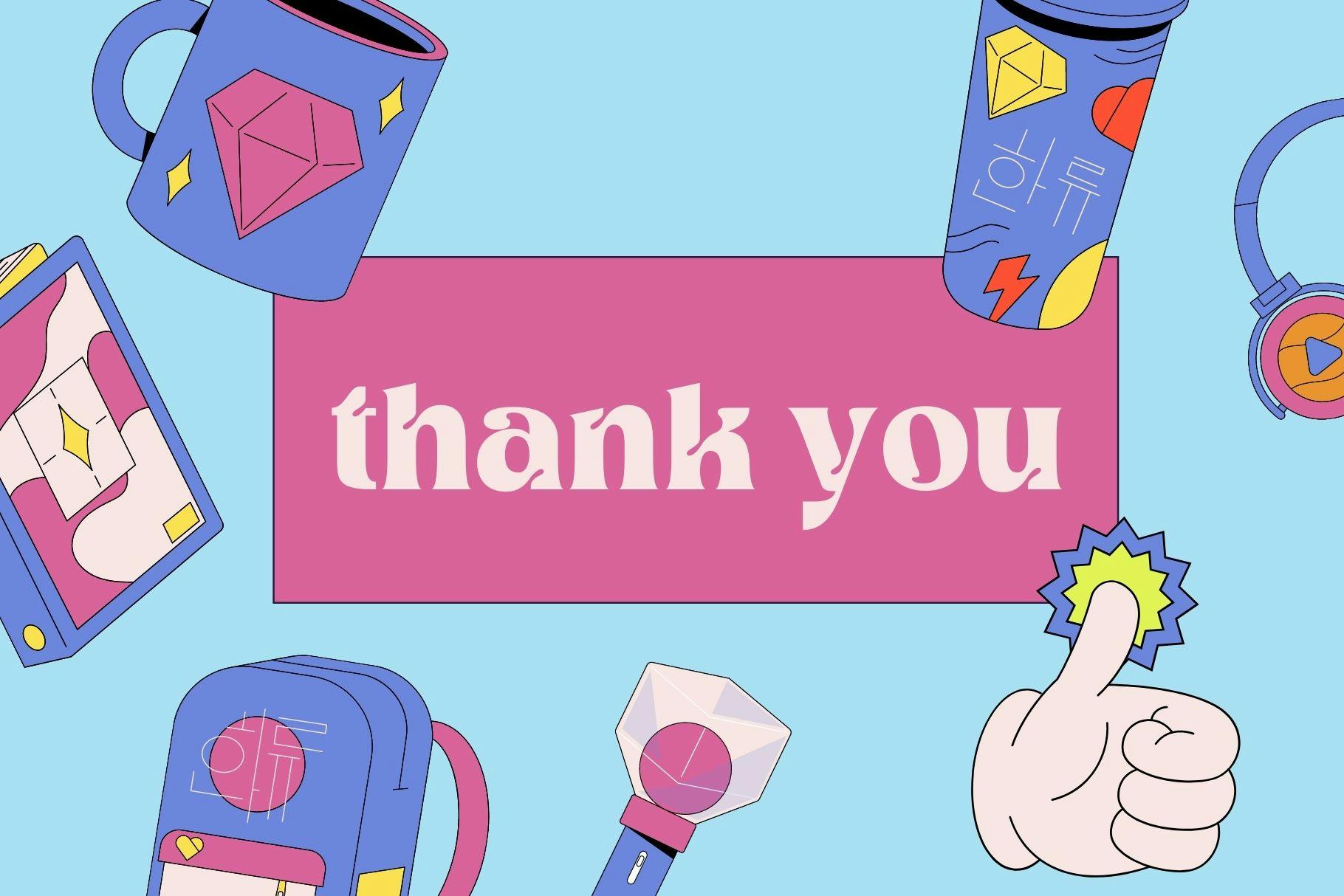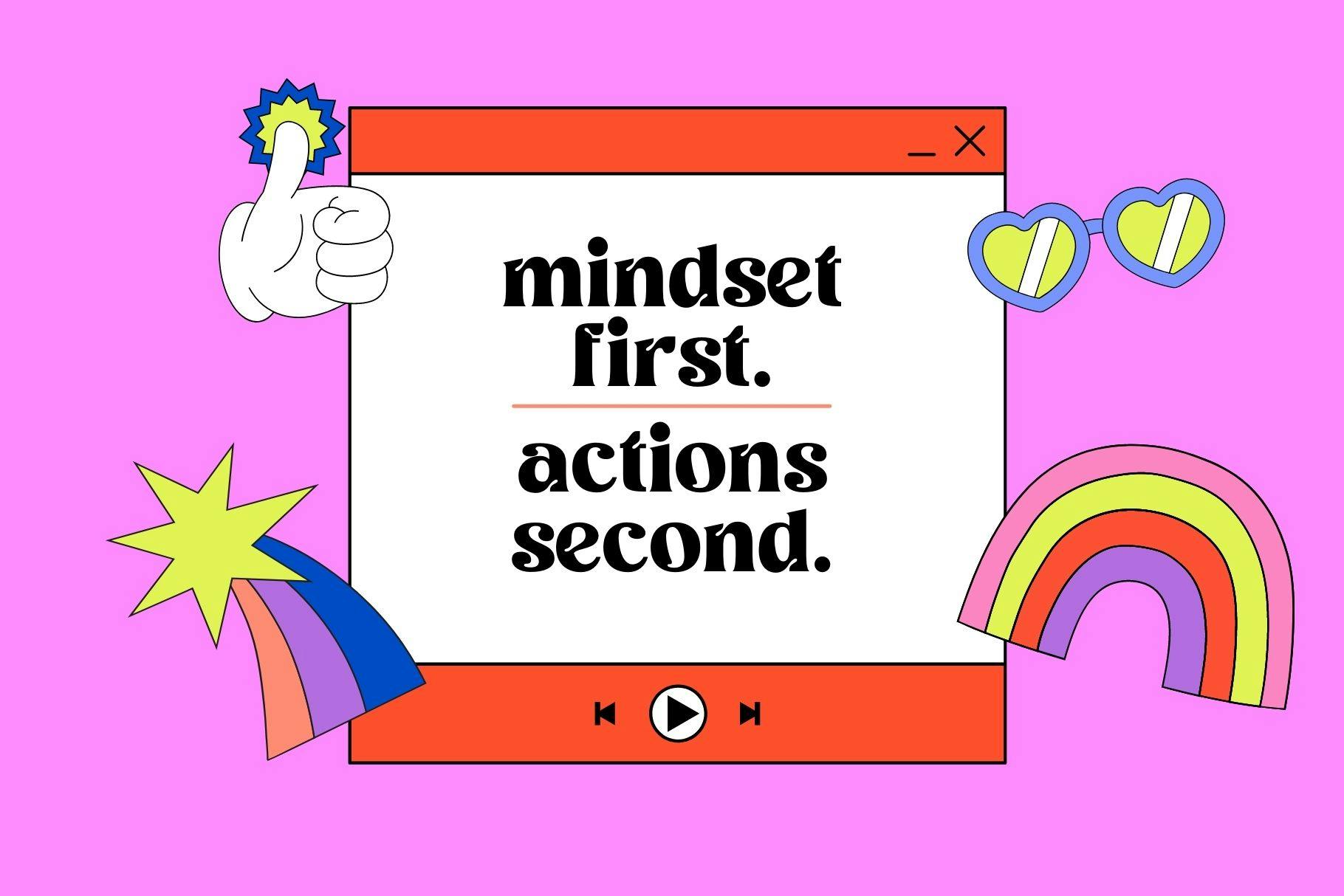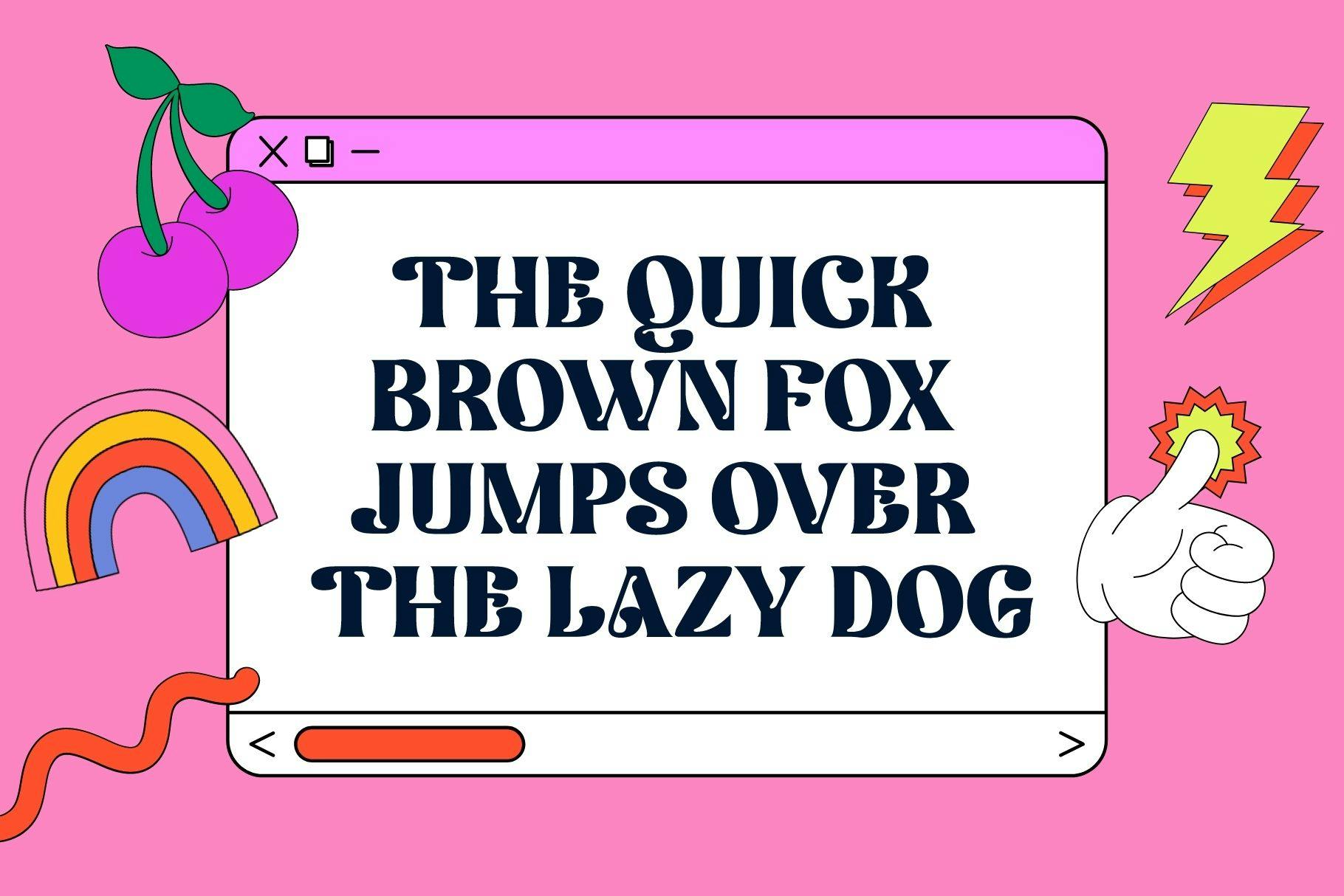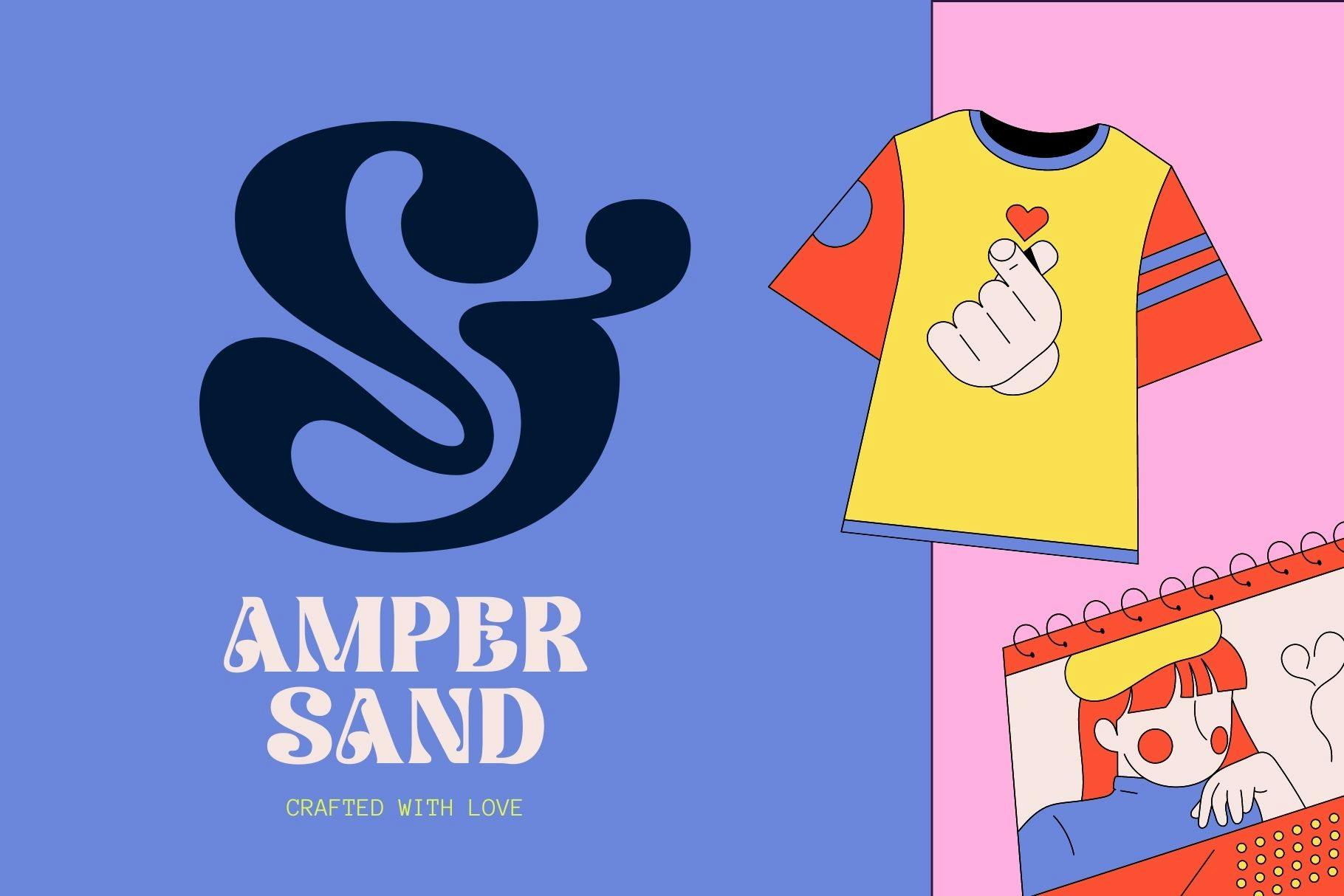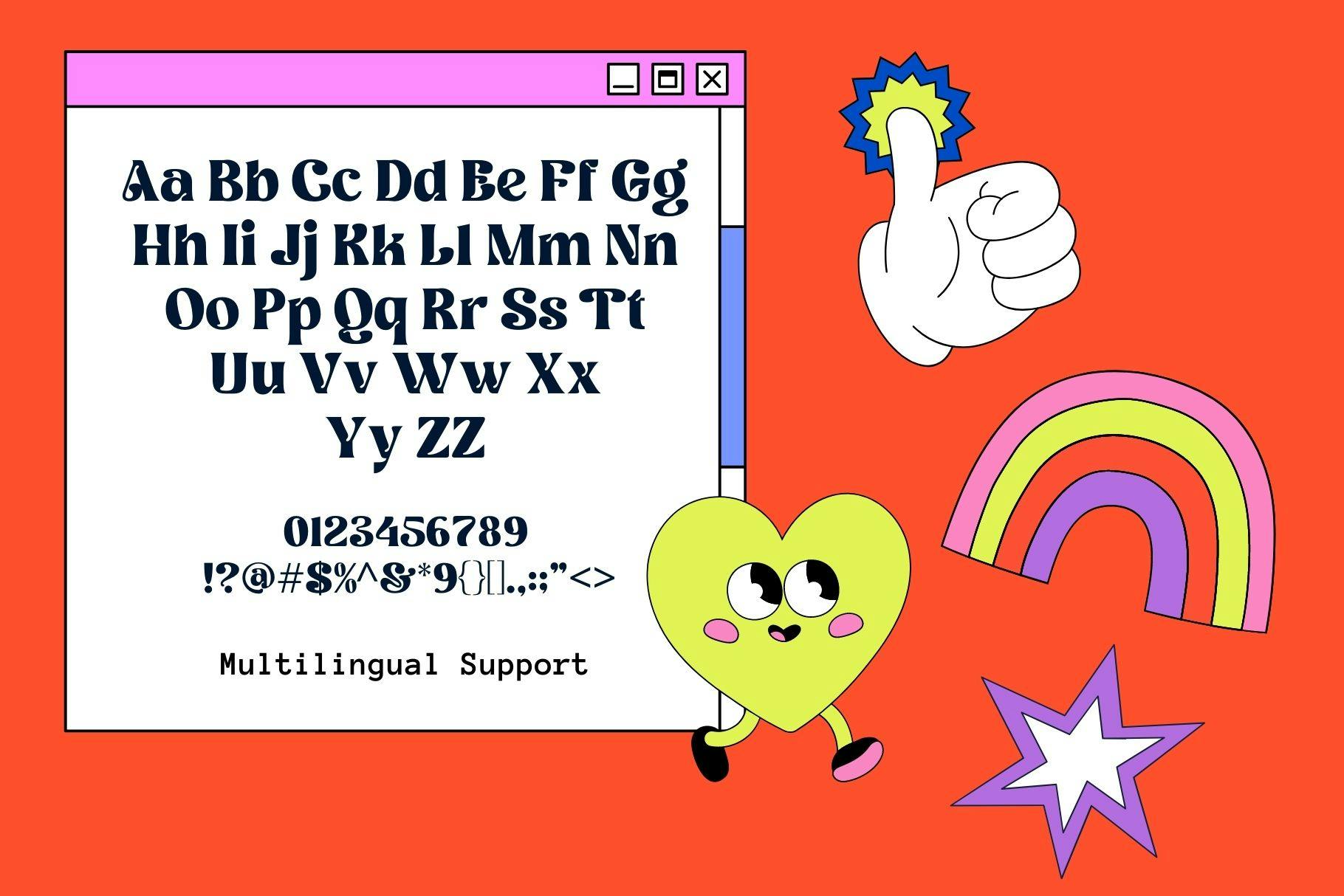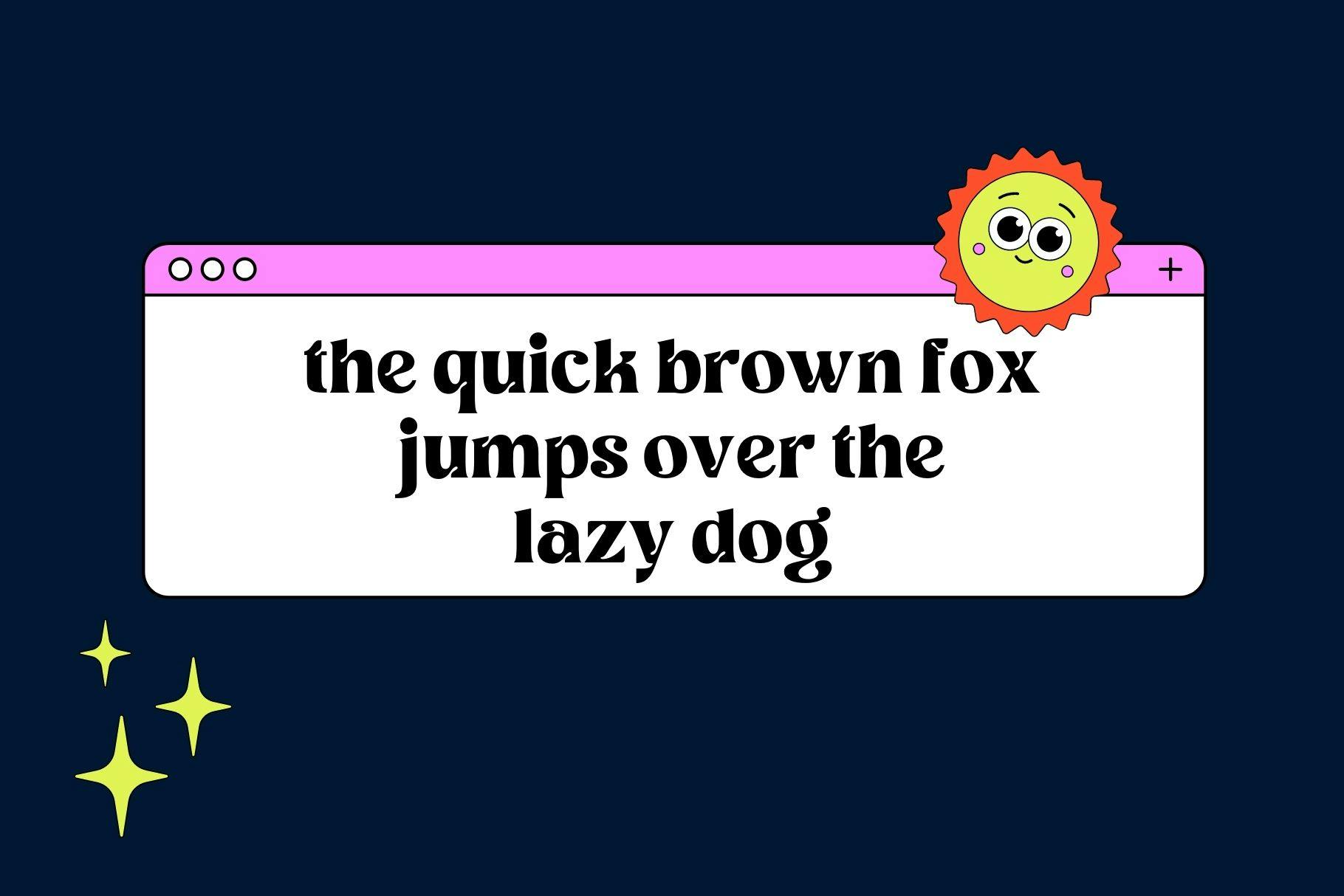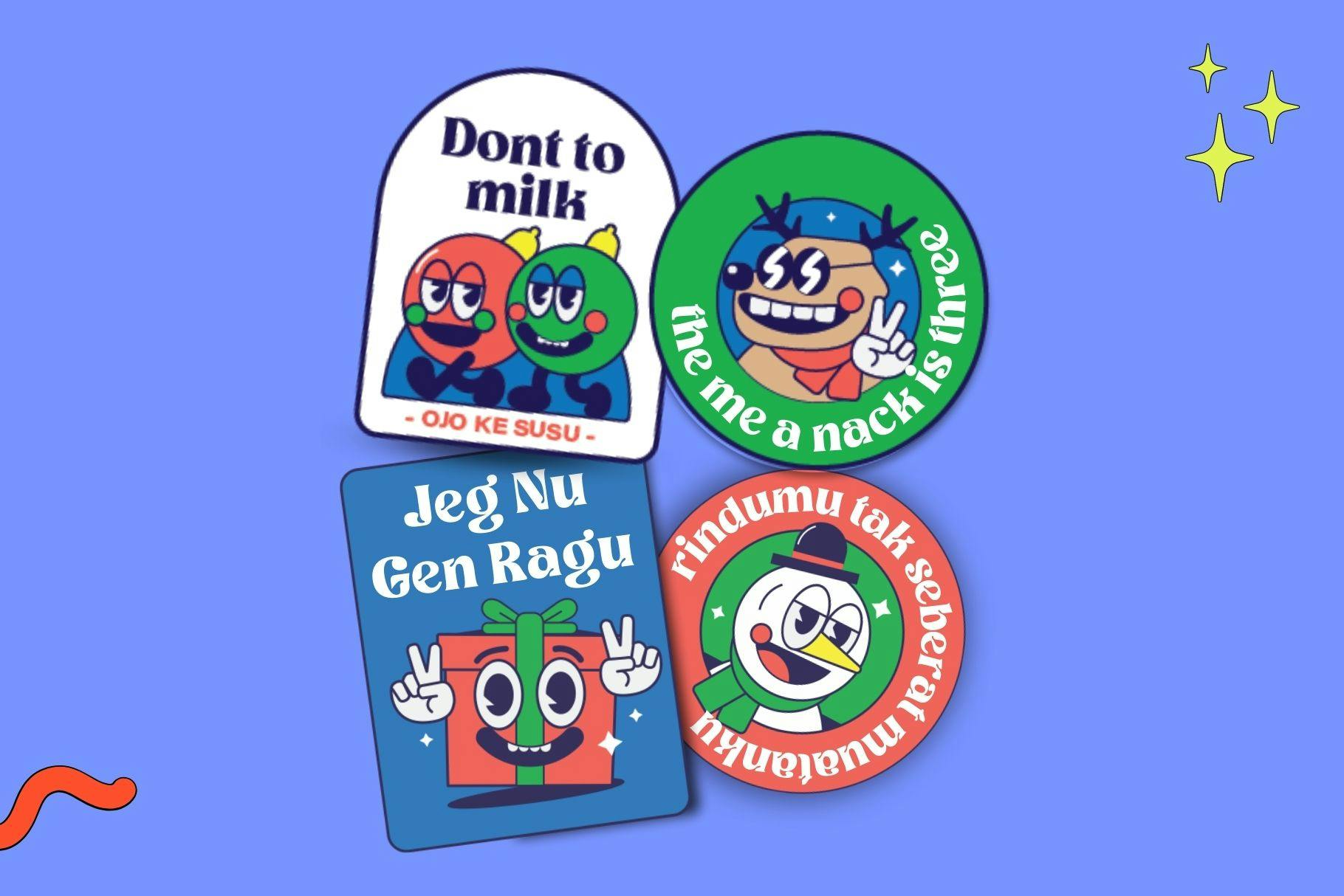
Retro Boldy، یک فونت بولد و شیک است که با الهام از دوران دهه 90 طراحی شده است.
فونت Retro Boldy هارمونی زیبایی را برای انواع پروژههای طراحی، از جمله لوگو و برندینگ، پستهای شبکههای اجتماعی، تبلیغات و طراحی محصولات ارائه میدهد.
این فونت شامل مجموعه کاملی از حروف بزرگ و کوچک، اعداد و نشانهگذاری، و نمادهای چند زبانه است.